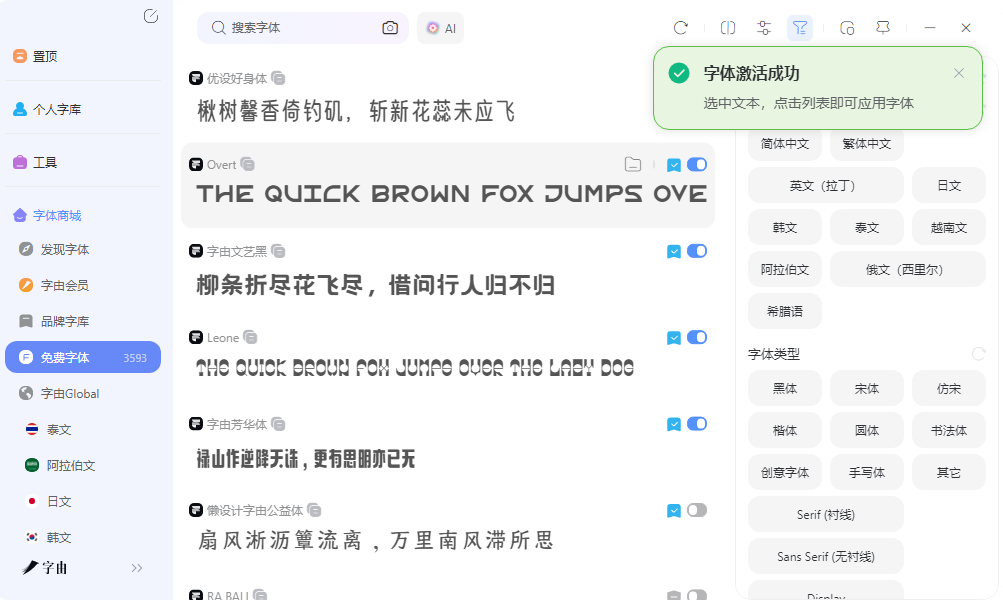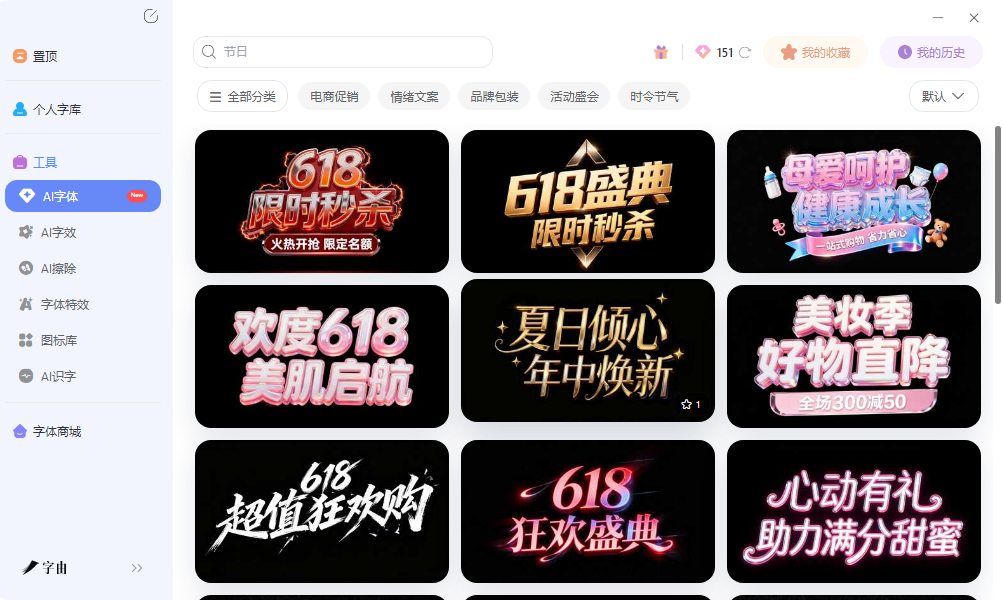
好的字体设计网站合集,做项目不愁找不到好字体
做设计项目时,找到一款合适的字体往往比设计本身还费时间。很多设计师的硬盘里塞满了从各处搜集的字体文件,安装包、压缩包、试用版混在一起,真到用的时候反而不知道哪个靠谱。现在有不少好的字体设计网站把这件事变得更系统,从找字体、管理字体到自己造字体都有覆盖。这篇文章整理了五个各有特色的平台,帮你把字体相关的工作流程弄清楚。
打开字由客户端,面对超过一万款字体的资源库,很多人第一反应是选择困难。而字由平台在设计浏览体验时考虑到了这个问题,左侧导航按基础书体分类,顶部有免费商用、风格、场景等多个维度的筛选条件,勾选后结果会实时收窄,不会出现漫无目的的翻页。
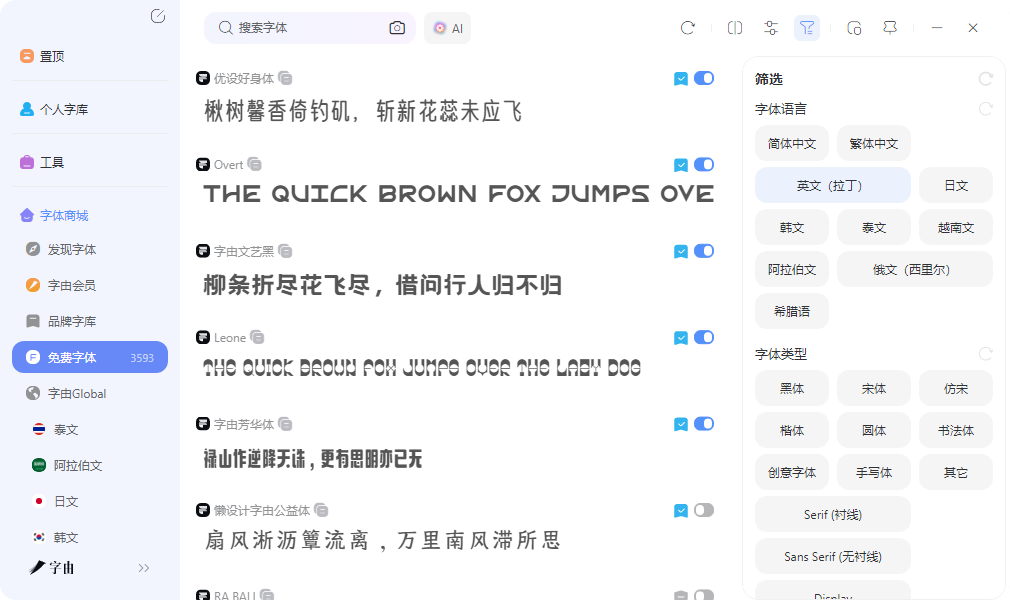
字体库的管理逻辑和传统安装模式有很大不同。字由采用云端激活的方式,点击激活后字体直接出现在设计软件中,不在本地产生安装包,也就不存在字体文件散落各处、版本混乱的问题。对于经常需要在多台设备之间切换的设计师,这种云端管理的方式省去了反复安装卸载的麻烦,登录账号就能调用全部已激活的字体。
AI字体功能是字由主推出的一个特色模块。它和AI字效有所区别,AI字体更偏向整体风格渲染,比如将文字一键转换为水墨效果、鎏金质感、霓虹发光等视觉风格。操作上只需要选择模板、输入文案、点击生成,产出的是透明背景的PNG图片,可以直接拖入设计稿中使用。目前提供了数百种特效模板,覆盖国潮、书法、科技等多种风格方向。这个功能的实用性在于,它把原本需要在专业设计软件里层层叠加图层样式才能实现的复杂效果,简化为几次点击,对于项目周期紧张、需要快速出图的场景比较友好。
2、FontStruct
FontStruct是一款在线字体构建工具,操作方式很有创意。平台提供了一个网格化的编辑界面,左侧是几何形状的素材库,用户像搭积木一样把基本形状拼接组合,设计出属于自己的字体字形。整个过程不需要任何专业字体设计软件的基础,对初学者非常友好。
完成后可以直接下载生成的字体文件,也可以分享到平台的Gallery社区,和其他创作者交流。FontStruct的免费属性让它成为入门字体设计的一个低门槛选择,适合想体验字体创作过程、但不想投入大量学习成本的用户。对于教育场景或者纯兴趣驱动的字体探索,这个工具的趣味性和可玩性都不错。
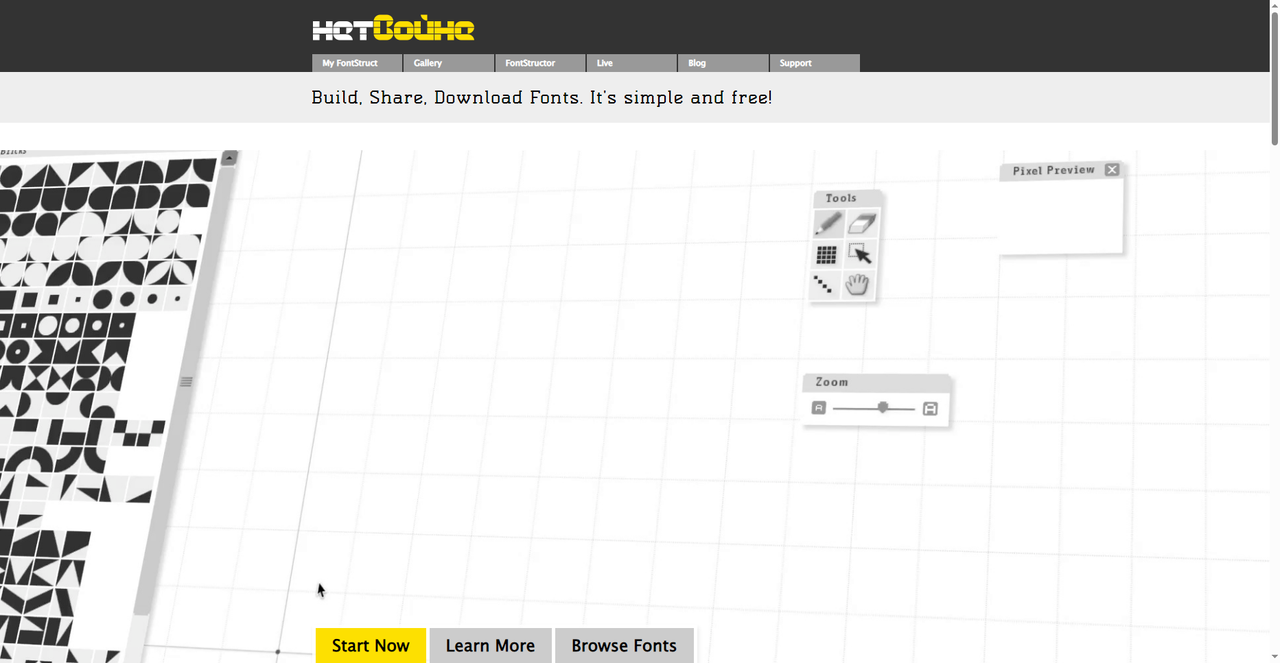
3、Calligraphr
Calligraphr的定位很独特,它解决的是"把我的手写笔迹变成可用字体"这个需求。操作流程简洁:下载模板纸,用笔在指定格子里写下字母和符号,扫描或拍照上传,平台会自动转换为TTF或OTF格式的字体文件。
这个功能对设计师和个人用户都有实用价值。设计师可以快速获得一套独一无二的手写风格字体,用于品牌项目或者文创设计;普通用户则可以把自己的字迹做成电脑字体,在文档和邮件中使用。平台支持免费体验,不需要信用卡,对新手比较友好。Calligraphr在好的字体设计网站中属于特色鲜明的那一个,它把字体创作从专业软件中解放出来,一支笔一张纸就能开始。
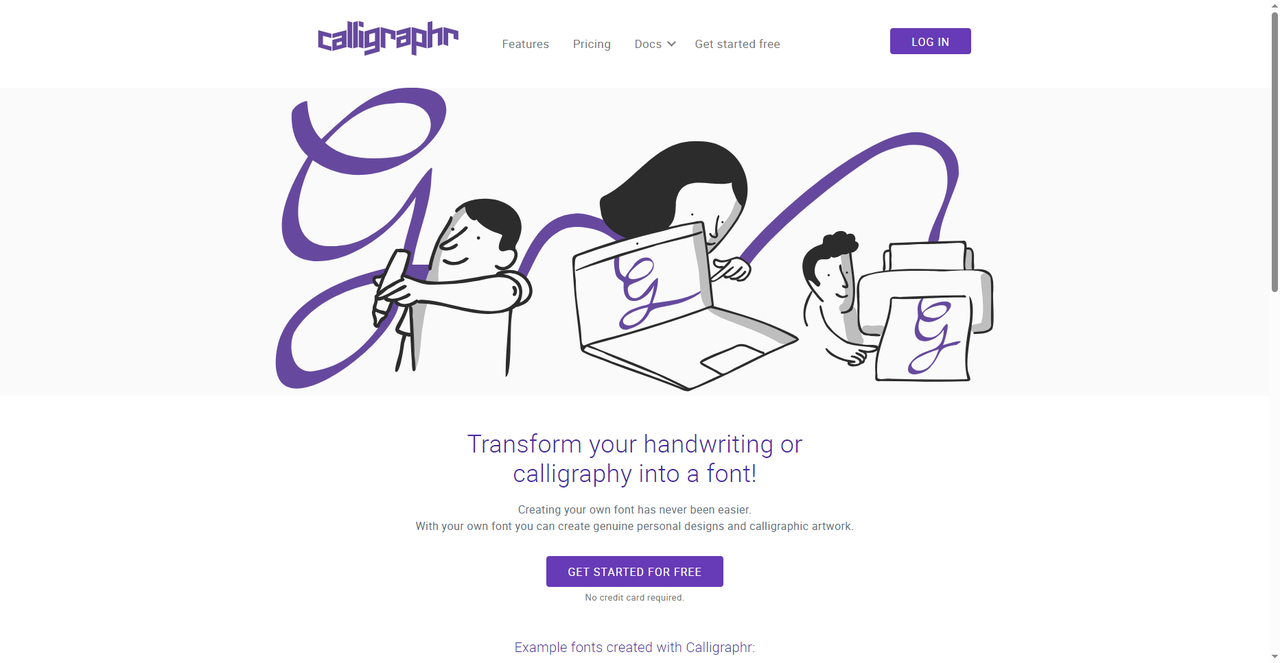
4、Glyphr Studio
Glyphr Studio是一款免费开源的网页字体编辑器,直接在浏览器中运行,不需要下载安装。界面设计参考了专业字体编辑软件的工作流程,但做了大量简化,降低了入门门槛。对于想学习字体设计基础、但又不想一上来就面对复杂专业软件的人来说,这是一个很好的起点。
工具支持基础的字体绘制、节点编辑、间距调整等功能,足以完成一套简单字体的设计。因为是开源项目,社区会持续贡献功能和修复问题,学习资源也比较丰富。如果你对字体设计感兴趣,想从最基本的字形绘制开始练手,Glyphr Studio是好的字体设计网站中值得 bookmark 的一个。
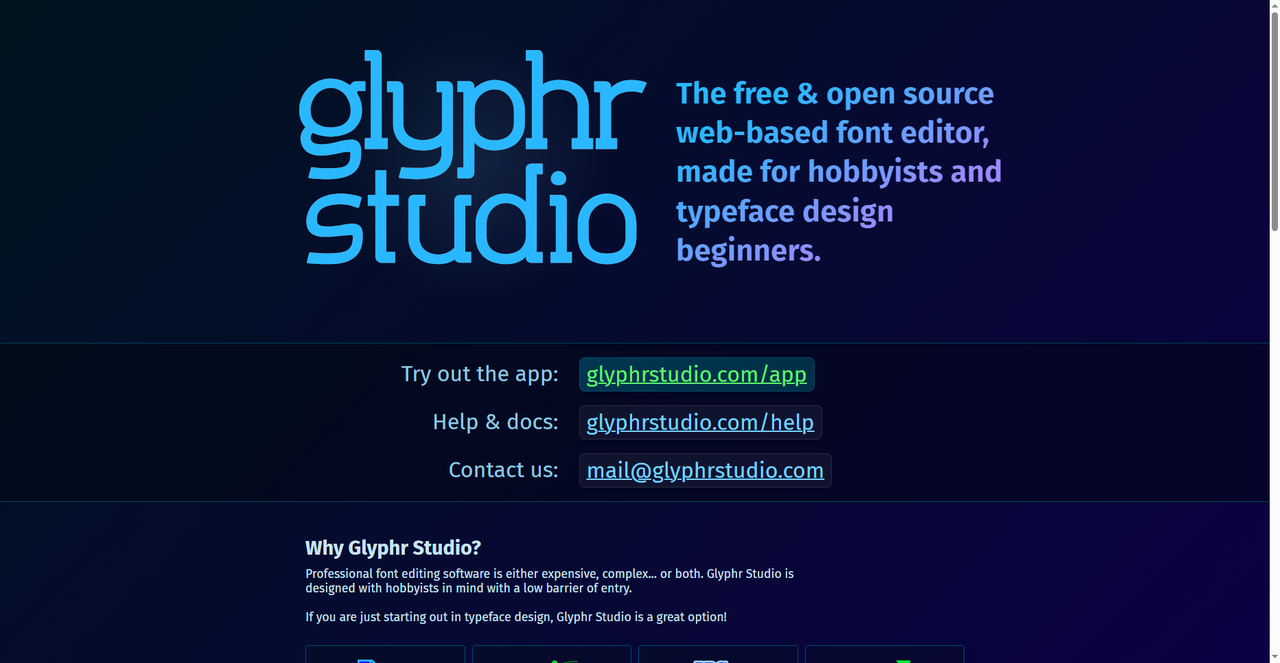
5、Fontfabric
Fontfabric是一家专业的字体设计公司,官网展示了多款高质量的商业字体家族,包括Fabric Grotesk等代表作品。和前面几个偏向工具或创作的平台不同,Fontfabric的定位是字体厂商,提供的是经过精心设计的成品字体资源。
平台上的字体风格偏向现代商业设计,字形质量高,字重和变体齐全,适合做品牌视觉识别系统或者高端印刷物料。Fontfabric也提供定制字体设计服务,对需要专属品牌字体的企业来说,可以直接委托设计。虽然这里的资源大部分是付费的,但对于追求独特性和专业度的项目来说,这些字体的设计水准和完成度是值得投入预算的。在好的字体设计网站中,Fontfabric代表了专业制作的标杆。